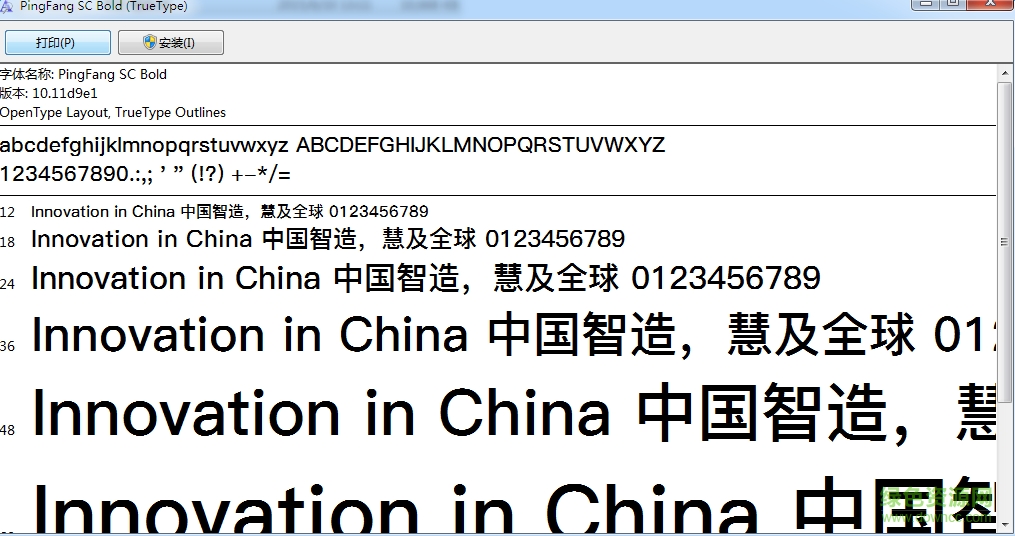
pingfang sc bold字體是蘋(píng)果公司推出的蘋(píng)方黑體粗體電腦字體,字體支持蘋(píng)果的動(dòng)態(tài)字體調(diào)節(jié)技術(shù),能夠自動(dòng)根據(jù)字號(hào)動(dòng)態(tài)調(diào)整字間距以及字體高度,從而達(dá)到最佳的閱讀效果,感興趣歡迎來(lái)綠色資源網(wǎng)下載!
pingfang sc bold是一款非常有特色的電腦字體,共有29951個(gè)字符。字符分布范圍:基本拉丁文、拉丁文-1補(bǔ)充、拉丁文擴(kuò)充-A、拉丁文擴(kuò)充-B、國(guó)際音標(biāo)擴(kuò)展、空白修飾字母、組合音標(biāo)附加符號(hào)、希臘文和科普特文、西里爾文、拉丁文擴(kuò)充增補(bǔ)、希臘文擴(kuò)充、一般標(biāo)點(diǎn)符號(hào)、上標(biāo)和下標(biāo)、貨幣符號(hào)、似字母符號(hào)、數(shù)字形式、箭頭符號(hào)、數(shù)學(xué)運(yùn)算符號(hào)、零雜技術(shù)符號(hào)、圈型字母數(shù)字、制表符、區(qū)塊組件、幾何形狀!